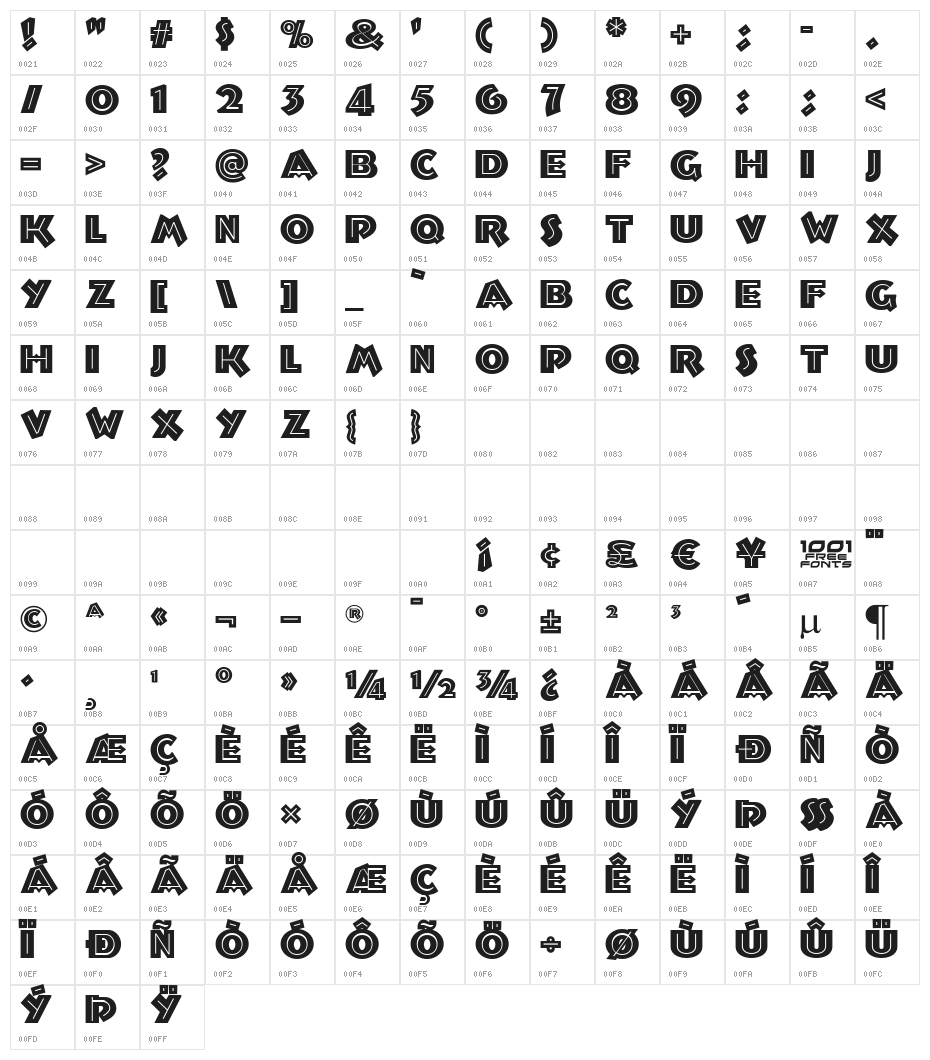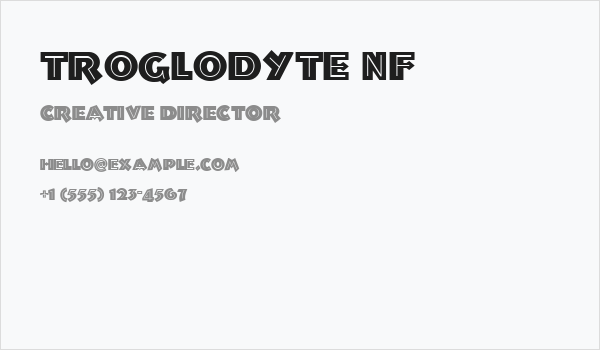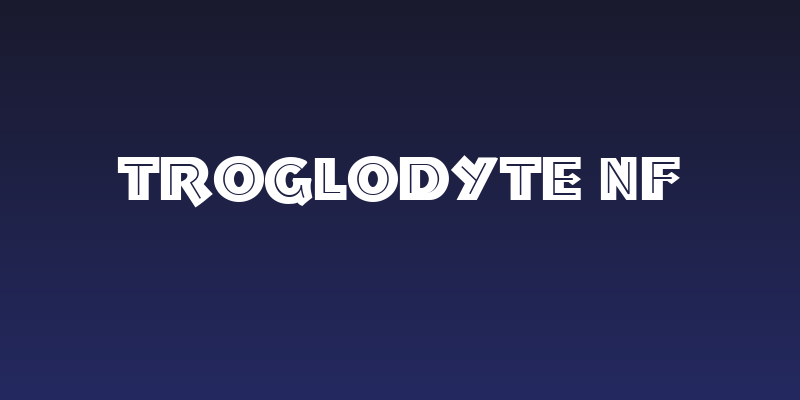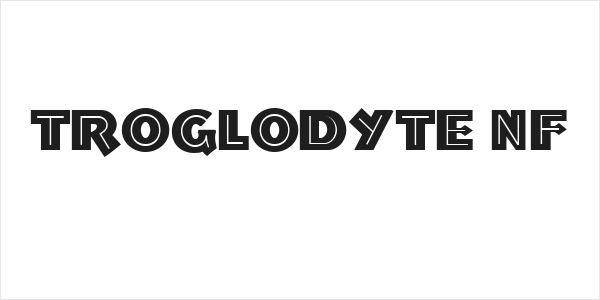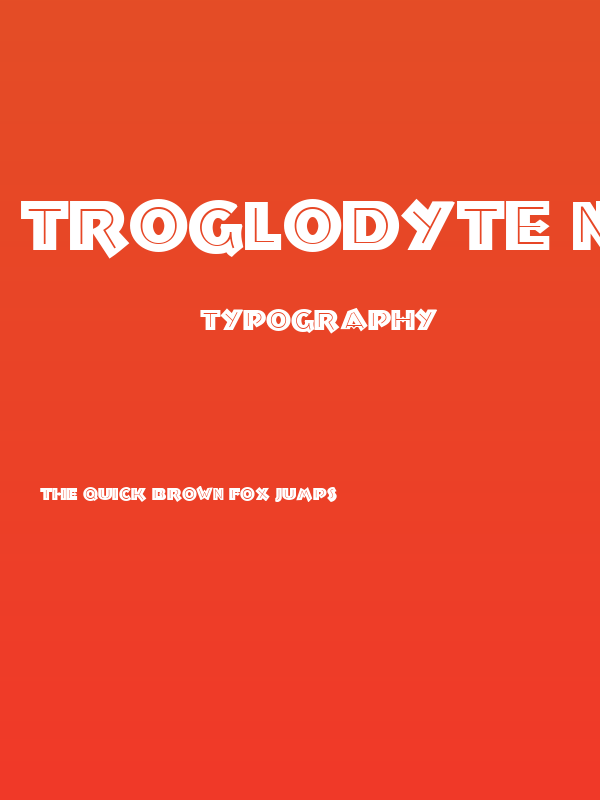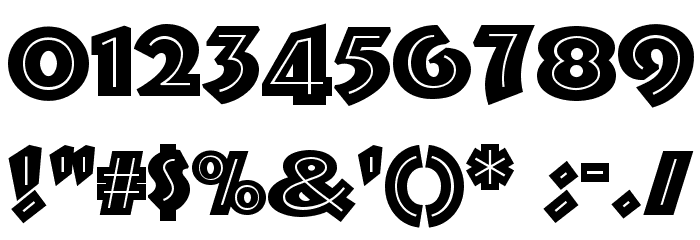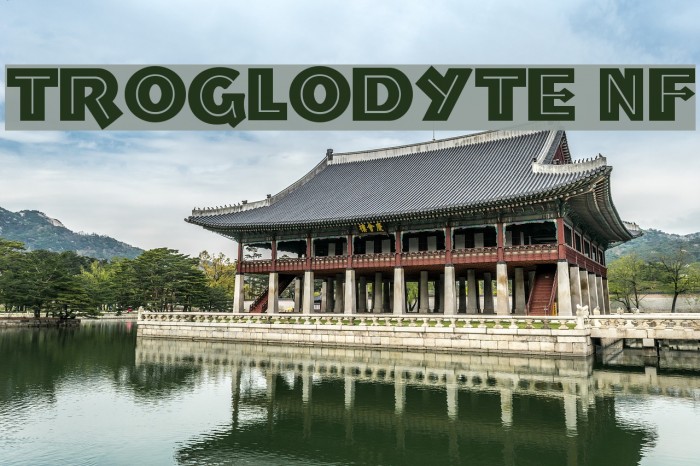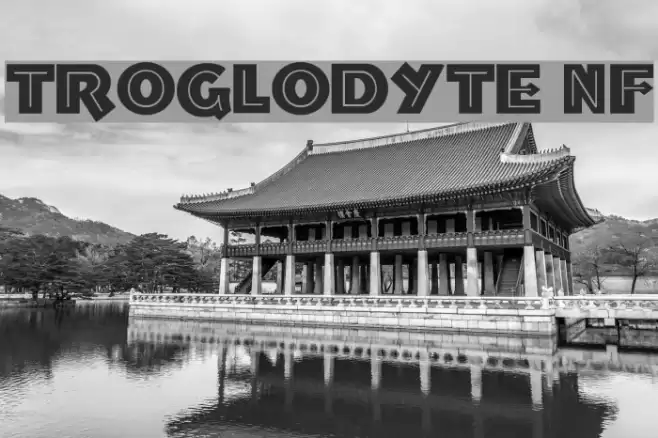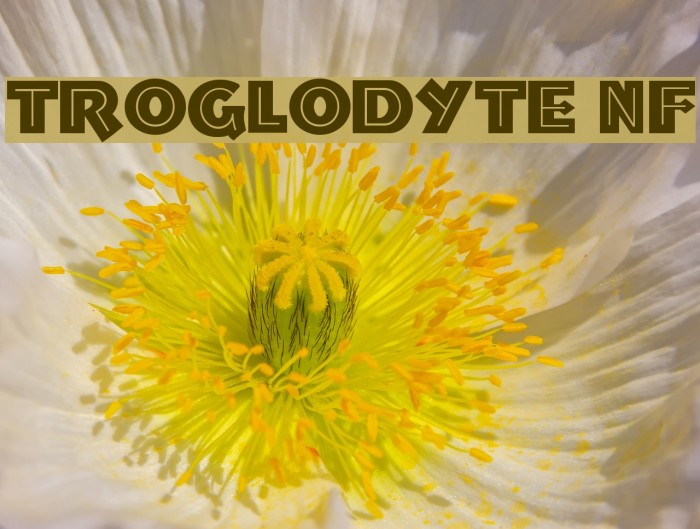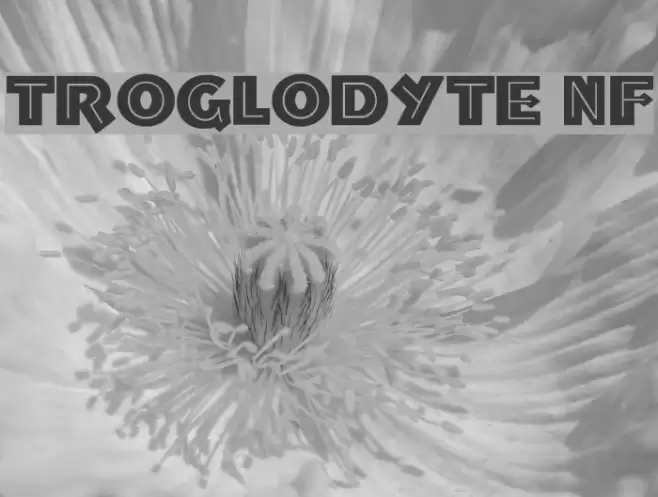
Troglodyte NF Font
| Категория | Outline |
| Общий стиль | Vintage |
| Рекомендуемые проекты | Ideal for vintage-themed posters, logos, and branding materials that require a strong visual impact. |